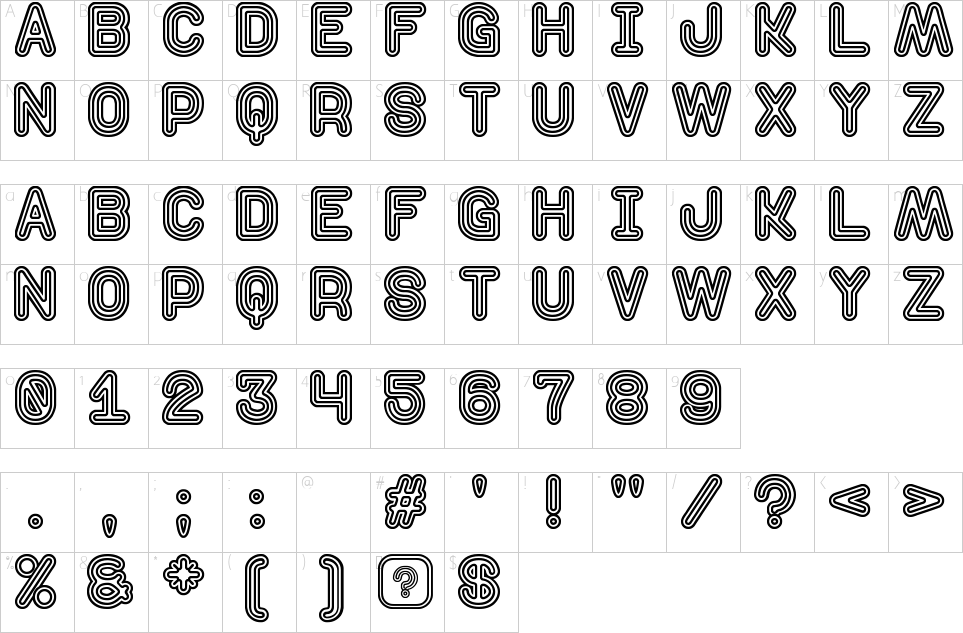
A Discoteque St é uma elegante e minimalista fonte que traz uma atmosfera descontraída e criativa, ideal para aqueles que procuram uma mistura sutil entre os anos 80 e 90. Desenhada pelo Southype, esta fonte fornece um contraste perfeito entre letras largas e detalhes delicados, tornando-a perfeita para aplicativos digitais como websites e designs gráficos para o Instagram ou as redes sociais. Seu estilo minimalista faz uma conexão direta com a cultura da noite underground dos anos 80 e 90, sem ser preso por estereótipos. As letras fluidas e curvilíneas têm um encanto que se adapta tanto à letra grande para publicidade quanto aos detalhes mais finos em design gráfico. A Discoteque St é uma escolha ideal para adicionar personalidade ao seu layout sem comprometer a legibilidade, tornando-a uma fonte indispensável para designers e criativos digitais.